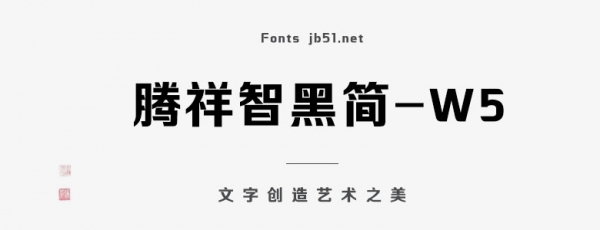
騰祥智黑簡(jiǎn)-W5是一款不錯(cuò)的藝術(shù)字體,由騰祥字庫(kù)出品,這款字體屬于騰祥智黑系列字庫(kù),該系列一共有六款粗細(xì),以W1至W6命名,這款字體是智黑系列中粗體一款,該字體筆畫簡(jiǎn)潔、硬朗、穩(wěn)重大方,適合應(yīng)用于藝術(shù)設(shè)計(jì)、平面宣傳設(shè)計(jì)、網(wǎng)頁(yè)設(shè)計(jì),書法字帖等領(lǐng)域,需要的朋友可以前來(lái)本站下載。
騰祥智黑系列字庫(kù)是騰祥睿黑系列字庫(kù)的兄弟篇,與睿黑風(fēng)格相近但排版效果迥異。該系列一共有六款粗細(xì),以W1至W6命名。智黑系列更強(qiáng)調(diào)了黑體的特征,筆畫簡(jiǎn)潔、硬朗、穩(wěn)重大方。塔形頓點(diǎn)、撇點(diǎn)賦予了智黑特殊的設(shè)計(jì)效果,使智黑又區(qū)別于傳統(tǒng)的黑體,既具有黑體的魅力又具有一定的裝飾特色,使黑體具有了靈活、生動(dòng)的特點(diǎn),從而形成自己鮮明的特色。本款字庫(kù)為智黑系列粗體一款W5,適用于大標(biāo)題、海報(bào)等設(shè)計(jì)類用字。